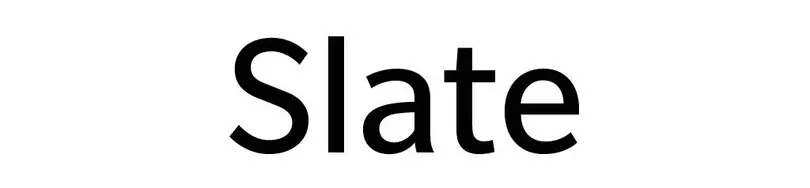
Polices pour l'industrie automobile
“ Les polices pour l'industrie automobile doivent être à la fois visuellement attrayantes et conformes à la marque, tout en étant exceptionnellement lisibles et faciles à lire d'un seul coup d'œil ”
Font For Cars
Absorbing information quickly is more than a convenience at 60mph. Fonts for cars must emit visual appeal and brand consistency, while being exceptionally legible and readable at a glance. This collection illustrates a sampling of typefaces that can be read easily to help keep drivers’ eyes where they belong — on the road.
Avenir Next
En concevant la police Avenir®, Adrian Frutiger s’est inspiré du passé et du futur. Frutiger a ajouté une touche d’humanisme organique à son design, libérant Avenir des aspects géométriques rigides des polices antérieures.
En 2004, en collaboration avec le designer de polices de caractères interne de Linotype, Akira Kobayashi, Frutiger a retravaillé la famille Avenir pour résoudre les problèmes d’affichage à l’écran. Le résultat a été la police Avenir Next. Le mélange d’éléments géométriques et humanistes contribue à la grande lisibilité de la police Avenir, la rendant idéale pour les environnements nécessitant une lecture rapide, tels que les panneaux et affichages des interfaces homme-machine (HMI) automobiles.
Burlingame
Relativement nouvelle, la police Burlingame® est un design robuste aux formes ouvertes et claires, offrant une lisibilité exceptionnelle, en particulier dans des environnements numériques restreints. Cette police incarne une qualité humaniste et artisanale, qui a été modifiée sur la base des résultats de recherches sur la lisibilité des interfaces de l’utilisateur automobiles commandées par Monotype, rendant Burlingame idéale pour le tableau de bord numérique de n’importe quel véhicule.
La police Burlingame fusionne des caractéristiques spécifiques en réponse aux besoins des affichages automobiles : terminaisons plates, angles vifs, panses super-elliptiques et espacement généreux. Ses formes simples et ses profondes découpes triangulaires contribuent également à assurer clarté et lisibilité sur les petits formats, en particulier sur les écrans basse résolution.
Frutiger
Adrian Frutiger était un designer de polices de caractères de renommée mondiale. Sa police homonyme est distinctive et idéale pour une grande variété d’utilisations. Initialement destinée à la signalisation aéroportuaire, la police Frutiger® reste très lisible à des distances et des angles variés. Frutiger est une police classique qui combine la lisibilité d’une police sans serif humaniste avec les lignes géométriques visuellement attrayantes d’une police sans serif grotesque.
La police Frutiger a été adoptée par de nombreuses entreprises et de nombreux gouvernements pour son look moderne et chaleureux. L’ouverture de cette police la rend extrêmement visible, et ses lettres distinctives évitent de se fondre les unes dans les autres.
Tipperary
La police Tipperary™ est une police monolinéaire humaniste sans serif aux formes claires et ouvertes. Ses caractères austères offrent une lisibilité exceptionnellement rapide, parfaite pour les interfaces de l’utilisateur. Pour créer cette police, de nombreux designs de polices classiques ont été réinterprétés et combinés. Il en résulte une police qui s’adapte parfaitement aux contraintes technologiques des écrans modernes tout en conservant les proportions et la forme qui en ont fait une police de choix dans l’impression.
Les lettres de Tipperary s’incurvent abruptement dans une géométrie presque carrée, ce qui en fait l’une des meilleures polices pour les environnements rapides tels que les compteurs automobiles, les écrans et les interfaces.
Daytone
La police Daytona™ a été conçue par Jim Wasco de Monotype en gardant à l’esprit la lisibilité. Elle présente des lettres robustes et carrées, basées sur des formes et des proportions humanistes. Les lettres de la police Daytona sont étroites, ce qui optimise l’espace et facilite la lecture. Ses coins arrondis, ses contreformes ouvertes et ses formes de caractères simples font de Daytona l’une des polices les plus lisibles de la bibliothèque Monotype.
La police Daytona fonctionne extrêmement bien dans presque tous les environnements d’affichage, y compris les interfaces de l’utilisateur automobiles, les tableaux de bord numériques et les GPS.
Akko
Dans une rencontre improbable d’adjectifs, les polices Akko™ et Akko Rounded sont couramment décrites comme « industrielles » et « élégantes », grâce à l’adoucissement par le designer Akira Kobayashi de ce qui a commencé comme un concept industriel austère. Le nom de cette police est dérivé des deux premières lettres du prénom et du nom de famille de son célèbre créateur.
Akko offre un design convivial, mais très contemporain, qui est hautement lisible tout en étant élégant. Le squelette minimaliste des lettres d’Akko réduit l’encombrement visuel qui peut se produire dans d’autres genres de design.
Une lisibilité parfaite. Un design inégalé.
Steve Matteson, Creative Type Director pour Monotype, a sélectionné cette collection pour présenter un échantillon de polices de caractères parfaitement lisibles pour que le regard du conducteur puisse rester là où il doit être : sur la route. En choisissant la bonne police de caractères pour votre tableau de bord ou votre interface de l’utilisateur, vous vous assurerez que votre affichage automobile sera hautement lisible et possèdera un design exceptionnel que votre public adorera.